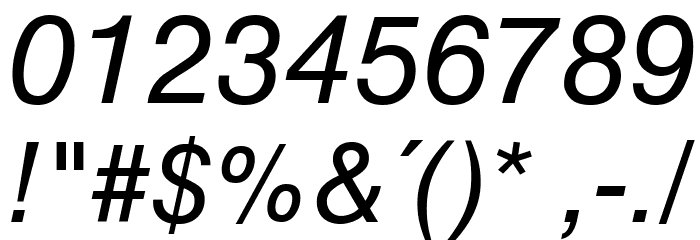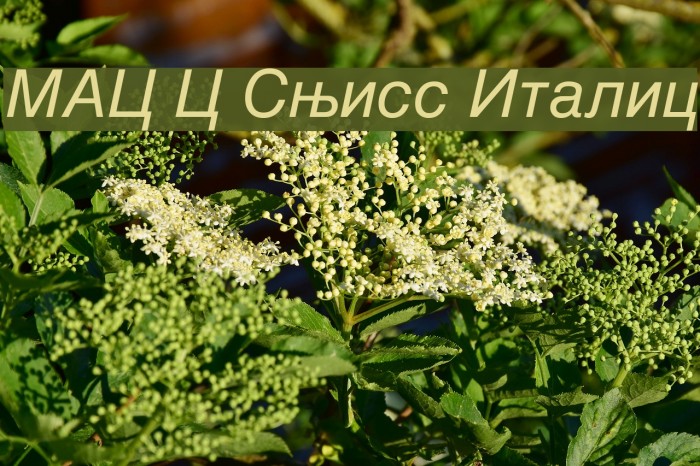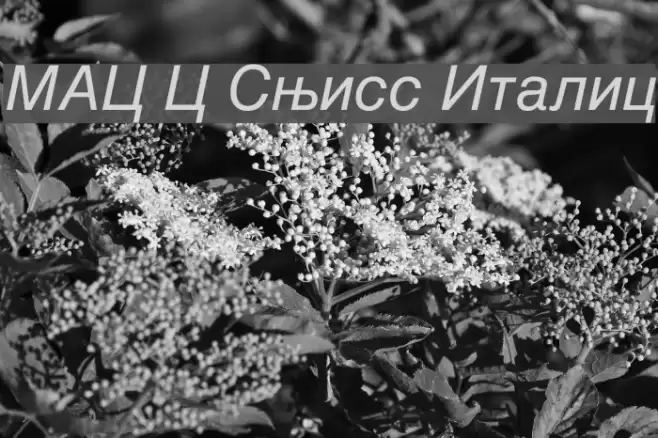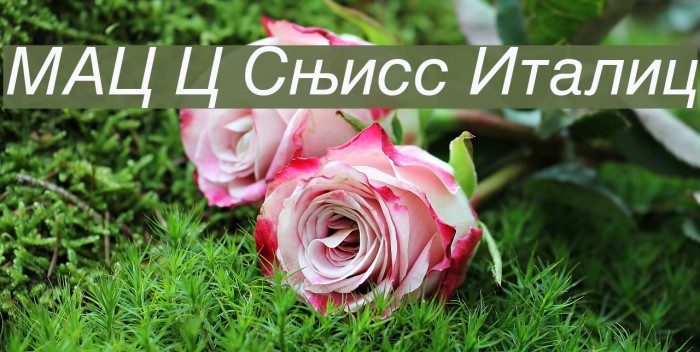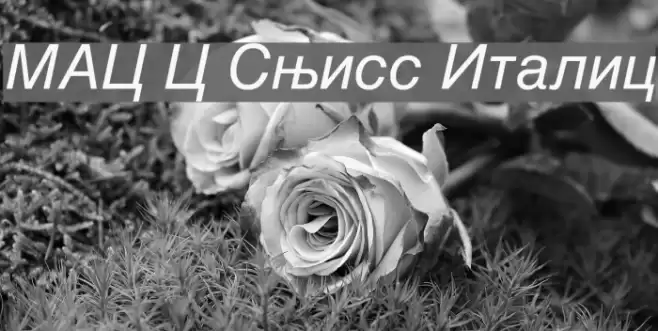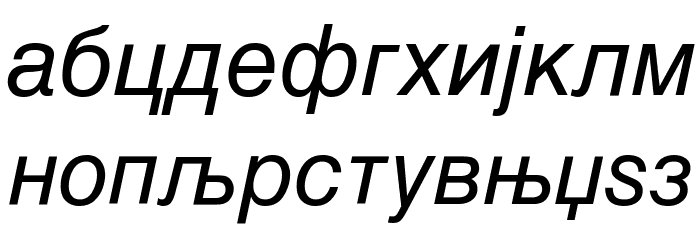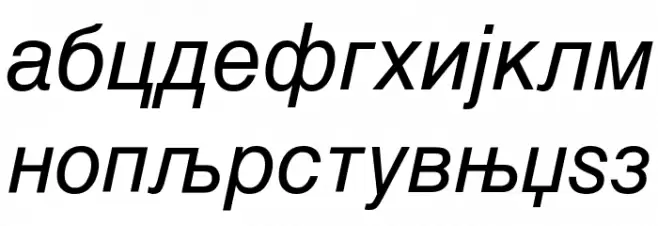
MAC C Swiss Italic Font
| Nombre | MAC C Swiss Italic |
| Peso | Italic |
| Categorías | Formal |
| Caso de uso | Headlines, Body text, Logos |
| Proyectos propuestos | Ideal for corporate branding, editorial design, digital interfaces, and signage where a modern and professional look is required. |